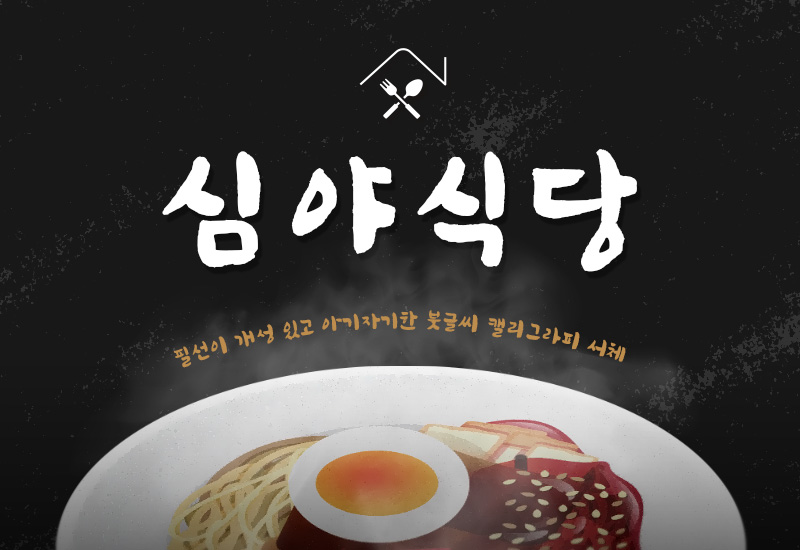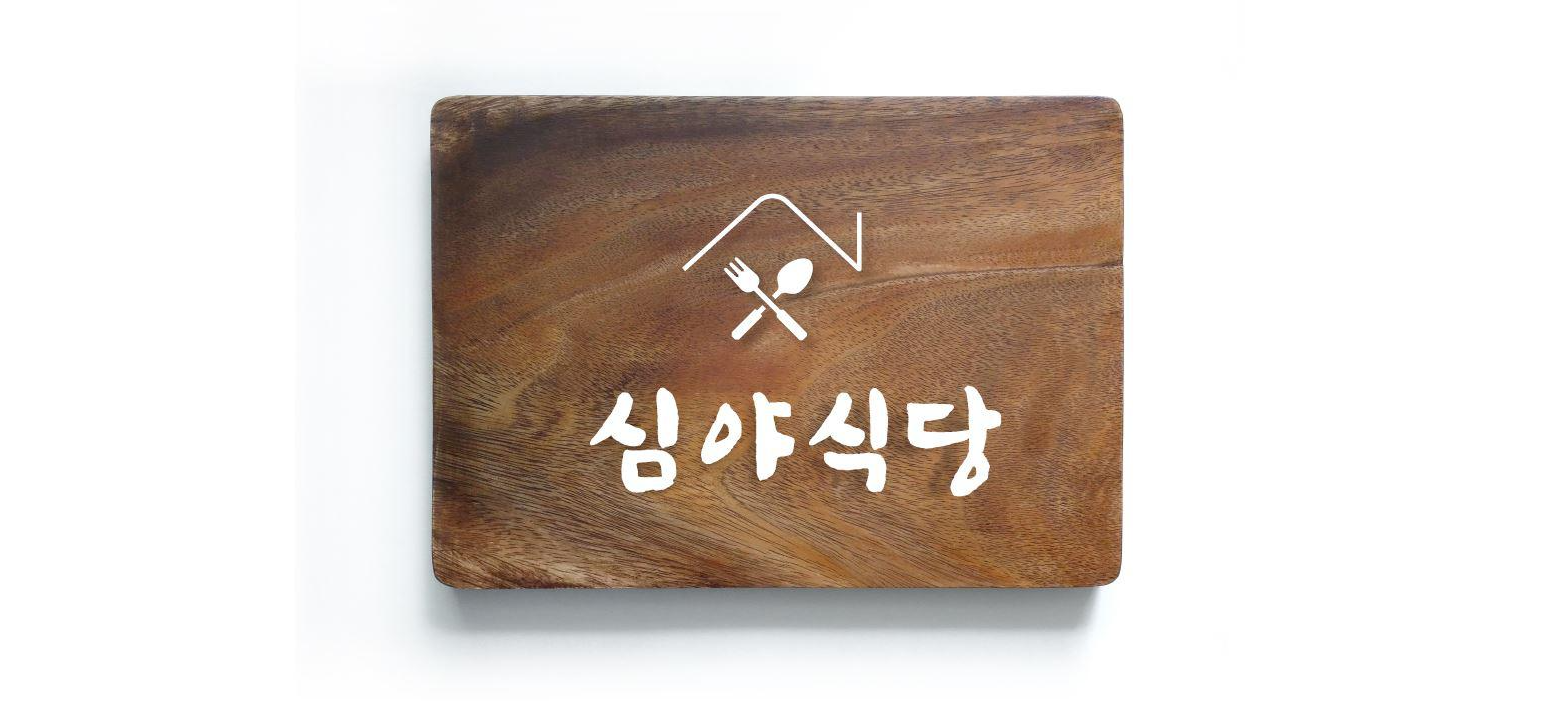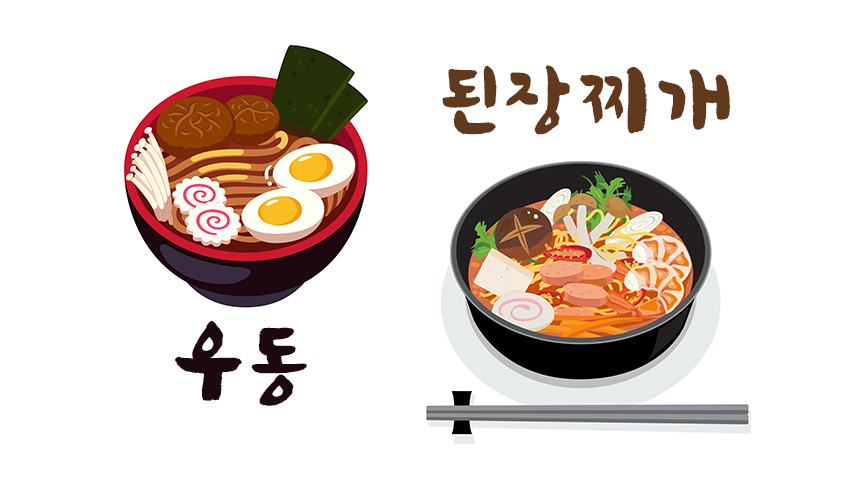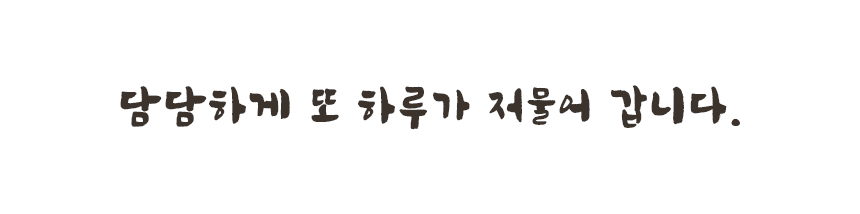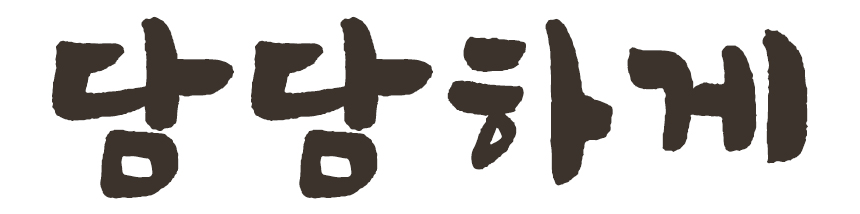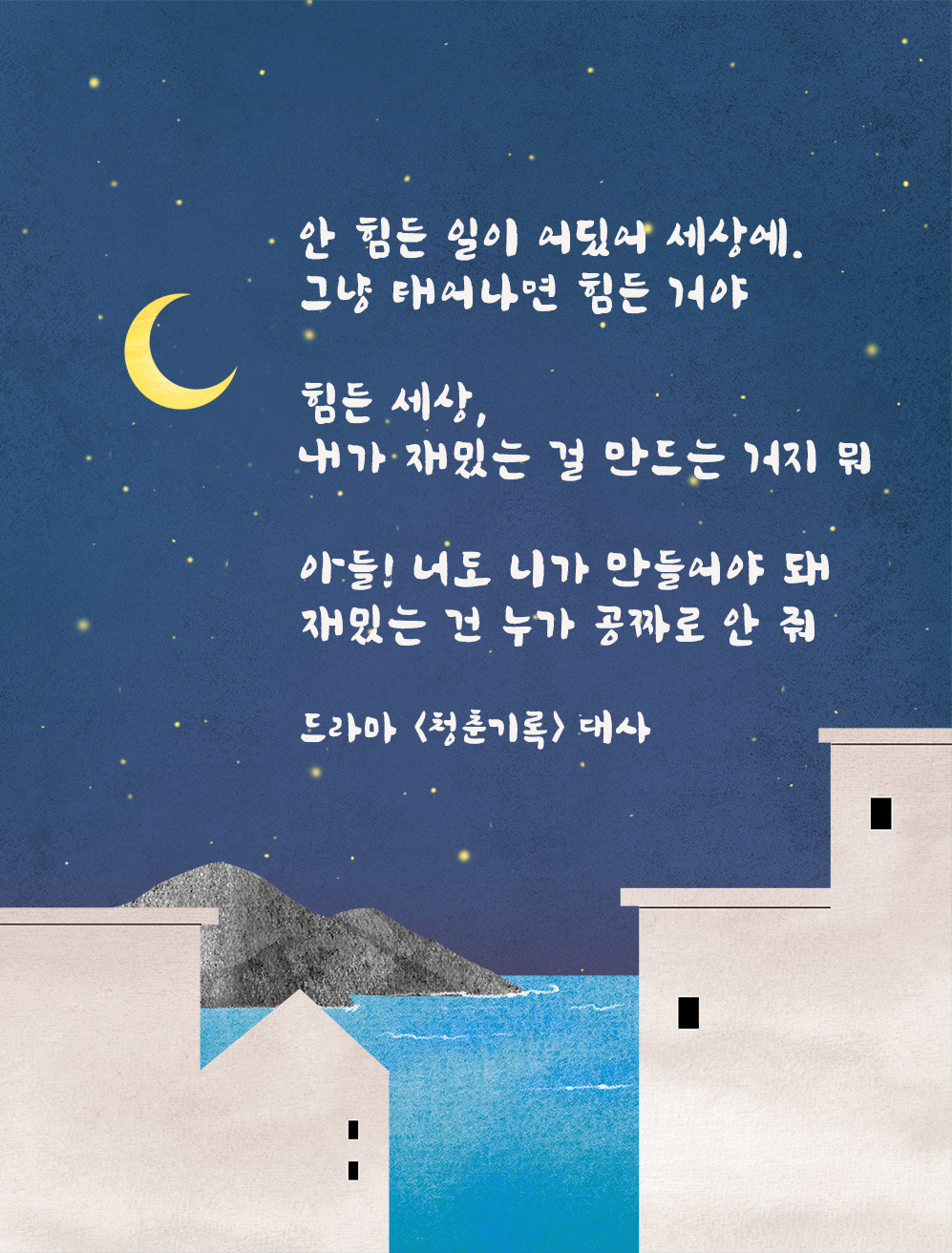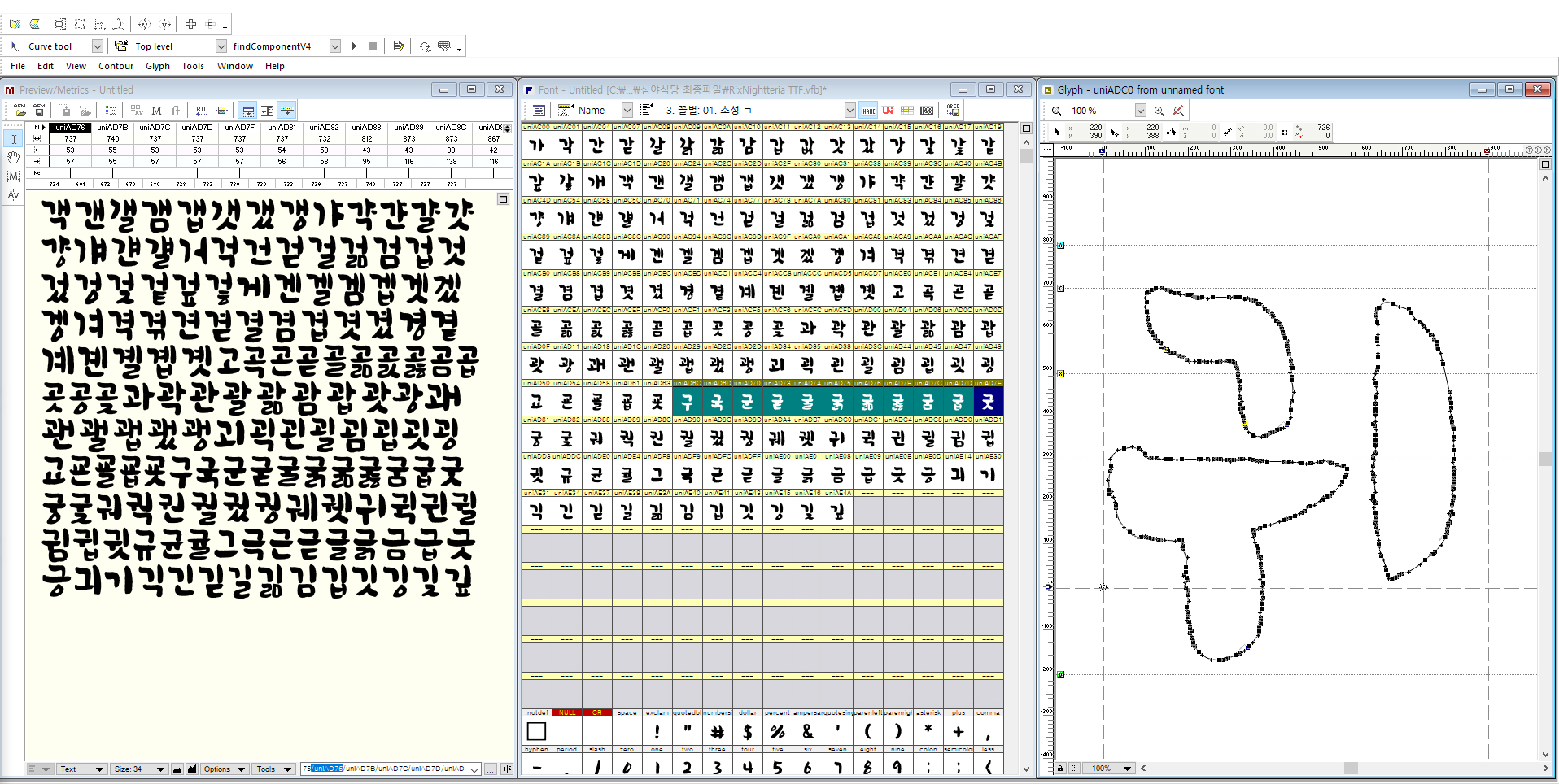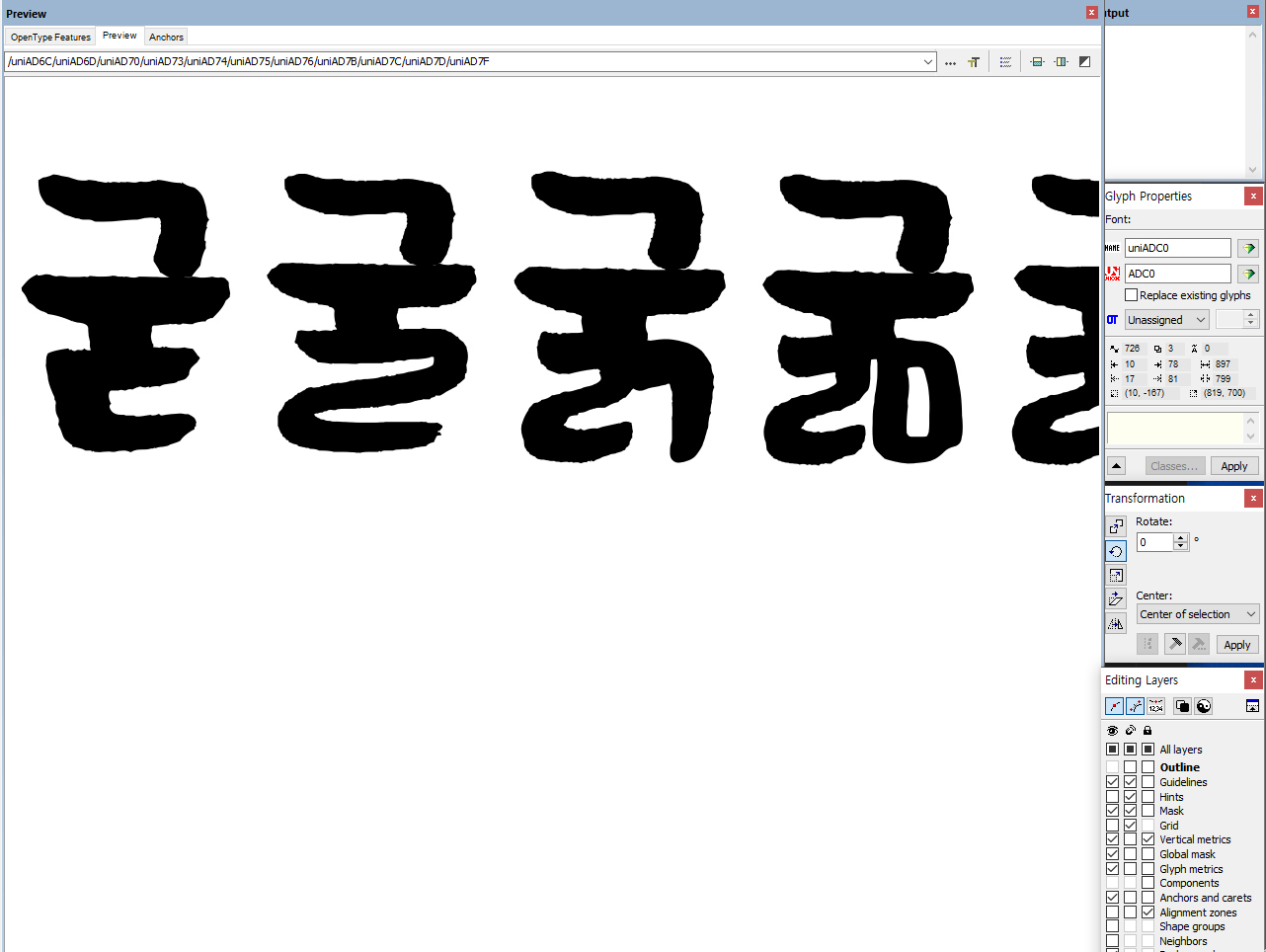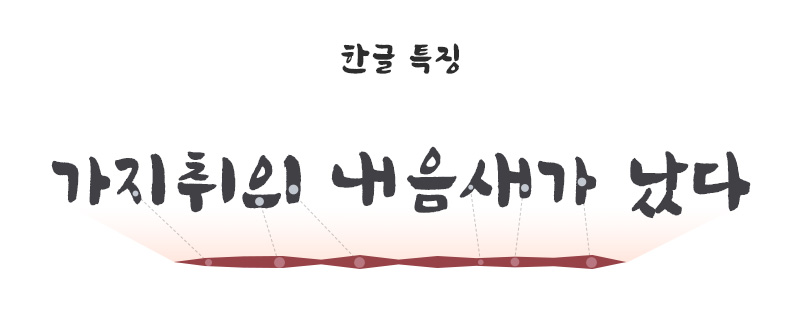
어느덧 가을바람이 쌀쌀해졌습니다. 서늘한 저녁, 온기가 도는 따뜻한 식당에서 후루룩 먹는 가락국수 한 그릇이 생각나는 시기가 다가오고 있네요. 이런 날씨와 잘 어울리는 따끈따끈한 11월의 신서체 「Rix심야식당」을 소개합니다. 어느 골목 식당 차림표에서 본 듯한 담백한 붓글씨 느낌이 물씬 나는 이 서체. 제작자인 이강우 디자이너에게 더 자세한 이야기 들어볼게요:)
폰트를 알려면 디자이너를 알아야지_폰트 디자이너 인터뷰
안녕하세요 이강우 디자이너님. 인터뷰로는 처음 뵙게 되었네요, 반갑습니다:) 먼저 간단하게 자기소개 부탁드려요!
안녕하세요 반갑습니다. 글자 쓰는 것을 좋아하다가 디자인까지 하게 된 이강우입니다. 붓으로 글자를 그리는 걸 좋아하는 편이에요.
이번에 작업하신 폰트가 벌써 릭스폰트의 두 번째 캘리그라피 폰트인데요, 어떻게 제작하게 되었나요?
Rix향기와 마찬가지로 기존의 캘리그라피 폰트를 일러스트 프로그램에서 조합해서 쓰는 것이 아니라 긴 글을 쓸 때에 편하게 쓸 수 있도록 폰트를 개발하는 것이었습니다. 물론 기존에 있던 캘리그라피 자음, 모음으로 어떻게 디자인하느냐에 따라 같은 소스를 쓰더라도 다른 폰트가 나올 수 있는 것 같은데요. 그런 의미에서 최대한 개성 있는 폰트를 만들기 위해 신경 써서 작업했습니다.
폰트명을 보고 정말 찰떡이라고 생각했는데요, 정말 심야식당 메뉴판에 나올 듯한데 어떻게 지은 이름인지?
처음에는 솔직히 막연히 생각하며 작업했어요. 어떤 느낌이 됐으면 좋겠다 하는 정도만 염두에 두고 제작했는데 제작하고 나서 이제 이름을 지어야 하니까 여러 가지 컨셉들을 고민하게 되었습니다. 그래서 원래는 광화문에 가면 보험회사 건물에 걸려있는 글귀 등에 쓰일 법하다는 생각이 들어서 그것도 만들어보고, 광고 카피에도 어울리겠다 싶어서 그것도 만들어 봤는데 한식, 일식 등의 가게 메뉴판이나 홍보물을 컨셉으로 만들어 보니 너무 찰떡이더라고요. 그렇게 컨셉을 발전시켜 나가다 보니 '심야식당'이라는 네이밍이 탄생하게 됐습니다.
정말 보이지 않는 고민의 과정이 많았군요! 이번 폰트를 제작하면서 새롭게 느낀 부분이나 어려웠던 부분이 있었다면?
저한테는 처음 해보는 작업이라 오히려 어렵지 않았던 부분이 없었던 것 같아요 :) 그래서 그런지 더 많이 배웠던 작업이었던 것 같습니다. 작은 것 하나도 잘못하면 모아놨을 때 크게 어긋나 보이는 등 폰트 제작이 어렵다는 것에 대해 간접적으로 체험한 유익한 경험이었다고 생각합니다.
폰트 디자이너로서 'Rix심야식당'의 가장 큰 매력 포인트를 꼽는다면요?
캘리그라피 폰트이긴 한데 흘림은 하나도 들어가 있지 않습니다. 그래서 좀 더 아기자기 한 매력이 있는 것 같고, 같은 초, 중, 종성을 공유하는 글자들 사이에서도 획의 굵기나 골격을 다르게 만들어서 조금 더 손글씨라는 느낌이 살아서 느껴질 수 있게끔 작업했습니다. 위에서 말씀드렸듯이 이런저런 컨셉을 연구해봤었는데요, 크게 진지한 분위기의 글귀만 아니면 어디에 써도 막 부담스럽고 그런 건 없는 것 같습니다. 그게 매력 포인트인 것 같아요.
앞으로 제작해보고 싶은 폰트나 생각해본 디자인이 있다면 무엇인지?
원래 글자에 매력을 느꼈던 부분이 붓글씨였습니다. 그래서 그런지 좀 더 세리프가 있거나 붓글씨 손글씨의 무언가가 들어있는 서체를 디자인해보고 싶다는 생각이 듭니다.
따뜻한 저녁 한 끼 같은, 폰트의 맛
이 폰트에서는 어떤 맛이 날 것 같나요? 두께감 있는 굵은 글씨가 면발과 닮아 우동 맛이 날 것도 같고, 제각각인 형태와 왠지 모를 따스함이 야채들을 툭툭 투박하게 썰어 넣고 끓인 엄마표 된장찌개 맛이 날 것도 같습니다. 호화롭고 비싼 레스토랑처럼 정갈하진 않아도 집밥이 생각나는, 작고 허름하지만 포근한 식당. 자유로운 모양의 두꺼운 글씨, 하지만 자세히 보면 한 자 한 자 정성이 담긴 서체 「Rix심야식당」은 마치 이런 식당에서의 저녁 한 끼 같다는 생각을 했습니다. 보기엔 쉽게 만들어 보이지만 그 안에 많은 애정이 담겨 있으니까요.
가을은 여느때와 같이 월급 통장처럼 스쳐가고 포근했던 바람은 어느새 찬기가 느껴지는데요. 겨울이 코앞까지 와 있는 기분이 듭니다. 피곤한 일과를 마친 직장인에게 추운 날 가장 먼저 생각나는 뜨끈한 국물처럼 몸과 마음을 녹여줄 따뜻한 우동 한 그릇 같은 서체꒰ᵕ༚ᵕ꒱
보고 있으면 마음이 몽글몽글 따뜻해지는 느낌이 들어요. 전체적으로 보면 짧뚱한 글꼴이 귀엽고 아기자기한 느낌을 주는데 크게 보면 먹의 번짐이나 자글거림이 표현되어 있어 붓글씨의 섬세함이 느껴집니다.
힐링을 전해줄게요.
따뜻하면서도 담담한 붓글씨의 표현 때문인지 이런 감성적이고 와닿는 문구와 참 잘 어울려요.
왠지 마음이 차분하게 힐링되는 일러스트와의 캐미도 만점! 매력 만점인 폰트 '◡'
요즘 길어진 코로나로 인해 우울감을 느끼는 분들이 많다고 하죠. 평범했던 일상을 갑자기 도둑맞아버린 기분.
이런 시기일수록 굳게 닫아놓은 마음 한편의 문을 누군가 살짝만 두드려줘도 위로가 될 수 있어요. 미소 속에 가려진 눈물을 보아주는 사람이 되길:)
폰트 제작기
알파벳 26자로 구성된 영어와는 달리 모음, 자음, 받침을 조합해 만들어지는 한글은 폰트 디자인을 할 때 아무래도 까다로운 글자가 아닐까 싶습니다. 이번 폰트는 더더욱 손글씨의 느낌을 살리기 위해 어떤 모음 자음이 만나는지, 어떤 받침이 들어가는지에 따라 같은 'ㄱ'도 각기 다르게 표현했어요. 다양한 디자인들을 보는 재미가 쏠쏠해요.
폰트 구성
한글의 경우 보통 11,172자 또는 2,350자로 구성되어 있습니다.
라틴(영문) 폰트는 94자로 구성됩니다.
실제 붓글씨로 쓴 것처럼 표현하기 위해 외곽선을 너무 깔끔하게 정리하지 않고 획의 굵기도 일정하지 않게 했어요. 먹을 머금은 붓으로 뭉툭하게 찬찬히 쓴 듯 자글거리는 표현을 그대로 살려 글씨의 맛이 더욱 살아나는 디테일!
붓으로 글자를 그리다.
붓으로 글자를 그리는 것을 좋아하는 이강우 디자이너의 서체는 붓으로 쓴 듯한 손글씨 느낌이 많이 납니다. 친근하면서도 깊이감이 느껴지고, 두께감이 각기 달라 리듬감이 느껴지는 것도 특징이에요.
위에 제작기에서도 잠깐 언급했지만 캘리그라피 서체라는 특성을 살려 각각의 글자 자소를 다르게 디자인했습니다. 겹치는 것 없이 각기 다르게 표현되도록 디자인하여 여러 형태의 자음, 모음을 조합해 만드는 캘리그라피의 특성을 그대로 재현했어요. 하나 하나 조합해보며 써야했던 캘리그라피, 이제 폰트로 쉽게 써보세요!
| Rix심야식당 적용 이미지 샘플
눈에 확 띄는 두께감과 아기자기한 형태로 로고나 각종 패키지, 사인물의 다양한 디자인에 활용하기 좋습니다. 일문 느낌이 특히 잘 어울려서 일식집 나무 메뉴판에 찰떡같이 어울리죠. 앞으로 여러 가지 디자인을 통해 Rix심야식당 폰트를 만나보게 되면 좋을 것 같네요!
마지막으로 드라마 <심야식당> 속 명대사와 함께 글을 마쳐봅니다. 모두가 늦었다고 생각한 78세 나이에 붓을 잡고 그림을 시작한 모지스(Grandma Moses) 할머니도 말씀하셨듯이 무엇을 시작하기에 늦은 나이란 없습니다. 사람마다 각자의 타이밍이 다르고 때가 다른 거예요. 나의 타이밍이 왔을 때 준비가 잘 되어 있다면 훨훨 날 수 있을 거라는 거.
감성적인 문구와도 잘 어울리는 「Rix심야식당」 폰트와 함께 안부를 건네는 따뜻한 연말 되시길 바래요:)